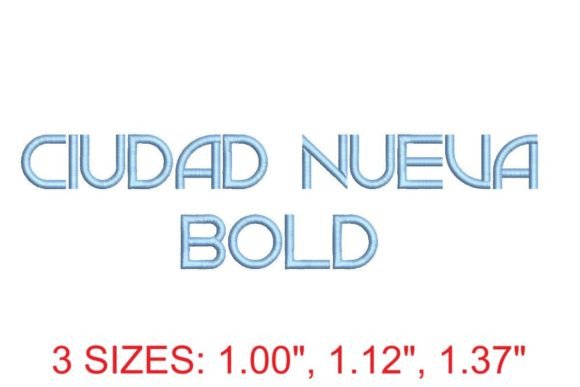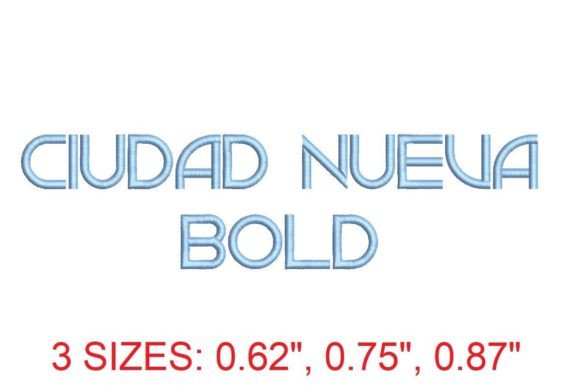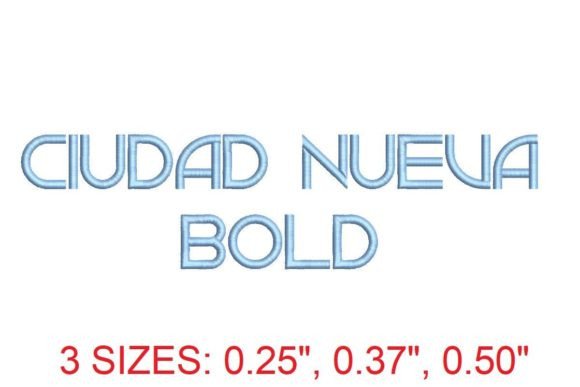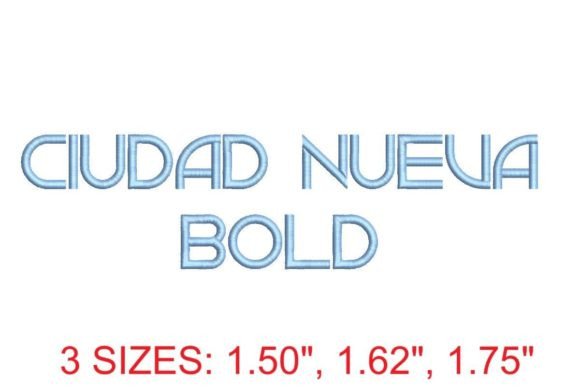
Ciudad Nueva Bold Embroidery Font
Mencari elemen desain yang tepat bisa jadi sulit, namun Ciudad Nueva Bold Embroidery Font menawarkan koleksi luar biasa yang akan langsung meningkatkan kualitas karya Anda.
Dibuat dengan presisi, Ciudad Nueva Bold Embroidery Font menyediakan vektor yang bersih, tipografi yang halus, serta lisensi komersial untuk ketenangan pikiran Anda.
Baik Anda membuat produk POD (Print on Demand), undangan pernikahan, atau grafis media sosial, Ciudad Nueva Bold Embroidery Font adalah pilihan yang sangat ideal.